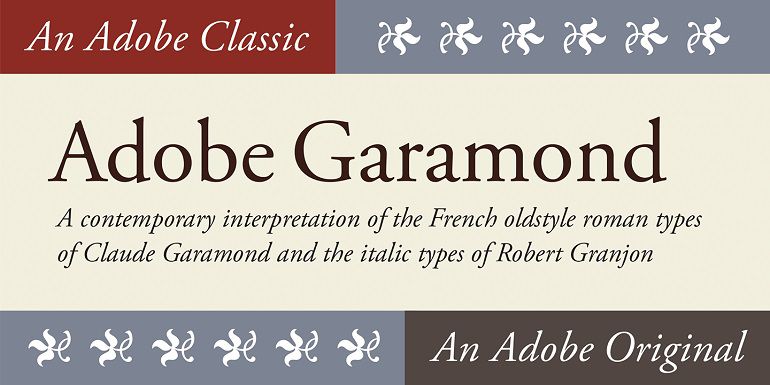
Stellen Sie sich Folgendes vor: Sie haben ein beeindruckendes Briefkopfdesign erstellt, aber irgendetwas stimmt nicht. Die Schriftart.
Es ist nicht nur ein Detail; es ist entscheidend für den ersten Eindruck Ihrer Marke. Hier beginnt die Suche nach den besten Schriftarten für Briefköpfe.
In einer Welt, in der jedes Pixel viel über Ihre Markenidentität aussagt, ist die Wahl der richtigen Schriftart nicht nur eine Designentscheidung; es ist eine Geschäftsstrategie.
Ich habe mich tief in die Welt der Typografie vertieft, von der Eleganz der Serifen bis zum schlanken Reiz der serifenlosen Schriftarten, um Ihnen einen Insider-Einblick in die Auswahl der Schriftarten zu geben.
Dieser Artikel ist nicht nur eine Liste; es ist eine Reise durch die Typografie in der Unternehmensidentität und die Auswirkungen der Schriftartwahl auf das Branding.
Am Ende haben Sie nicht nur eine Handvoll Top-Empfehlungen für Schriftarten, sondern auch ein tiefes Verständnis dafür, wie Schriftartenkombinationen für Geschäftspapiere und Trends in der Briefkopftypografie Ihre Marke aufwerten können.
Ob Sie ein Fan der Klarheit von Helvetica oder der Autorität von Times New Roman sind, dieser Leitfaden bietet für jeden etwas. Machen Sie sich bereit, Ihre Briefköpfe von gewöhnlich zu unvergesslich zu verwandeln.
Die besten Schriftarten für Briefköpfe
| Schriftartname | Designstil | Lesbarkeit | Am besten für | Notizen |
|---|---|---|---|---|
| Quilty Light | Dekorativ | Mittel | Kreative Branchen | Leicht und ausdrucksstark |
| Karoll Modern Serif | Modern/Dekorativ | Hoch | Professionell/Modern | Hoher Kontrast |
| Addington | Übergangs-Serif | Hoch | Unternehmen/Recht | Sophistiziert, altmodisch |
| Garamond | Alt-Serif | Hoch | Verlagswesen/Traditionell | Klassisch und elegant |
| Times New Roman | Übergangs-Serif | Sehr hoch | Geschäft/Allgemeiner Gebrauch | Allgegenwärtig und formell |
| Quiche Sans | Display Sans-serif | Mittel | Mode/Luxusmarken | Hoher Kontrast und schick |
| Mansory | Geometrisch Sans | Mittel | Technik/Moderne Unternehmen | Sauberes, modernes Aussehen |
| Hanken Sans Typeface | Neo-grotesk Sans | Hoch | Start-ups/Moderne Nutzung | Einfach und klar |
| Helvetica | Neo-grotesk Sans | Sehr hoch | Unternehmen/Universell | Neutral und vielseitig |
| Arial | Grotesk Sans | Sehr hoch | Geschäft/Allgemeiner Gebrauch | Weit verbreitet & lesbar |
Empfohlene Schriftarten für Geschäftsbriefe
Lassen Sie uns in das Herz der Sache eintauchen: die Suche nach den besten Schriftarten für Briefköpfe. Es geht darum, die Bühne für die Stimme Ihrer Marke zu bereiten, laut und deutlich zu hören.
Top Serif-Schriftarten
Quilty Light
Es ist wie das leise sprechende Genie im Raum. Elegant, aber zurückhaltend. Perfekt, wenn Sie Raffinesse wünschen, ohne es von den Dächern zu schreien.
Karoll Modern Serif
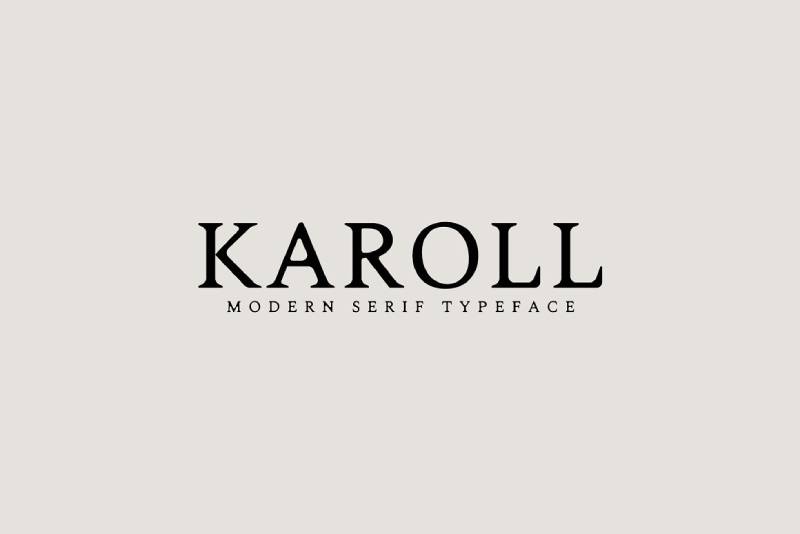
Stellen Sie sich eine Brücke zwischen altmodischem Charme und zeitgenössischem Chic vor. Diese Schriftart sagt: „Wir respektieren die Tradition, aber wir stecken nicht in der Vergangenheit fest.“
Addington
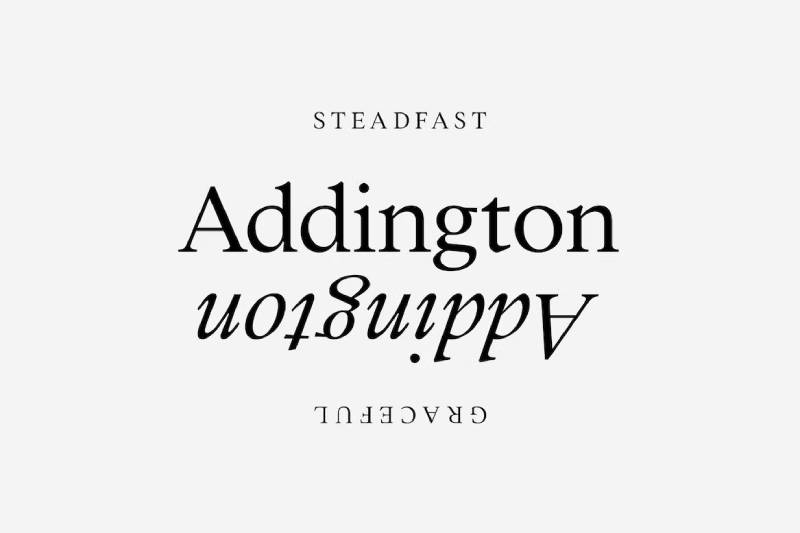
Es ist der Inbegriff des beruflichen Handelns. Denken Sie daran wie an Ihren Anzug für Geschäftstreffen.
Garamond
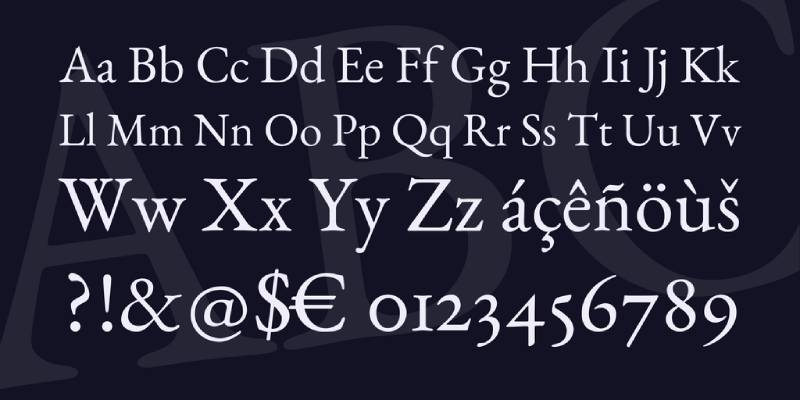
Ein Klassiker. Es ist wie der zeitlose Rat, den Sie von Ihrem Mentor erhalten haben. Zuverlässig, respektiert und immer stilvoll.
Times New Roman
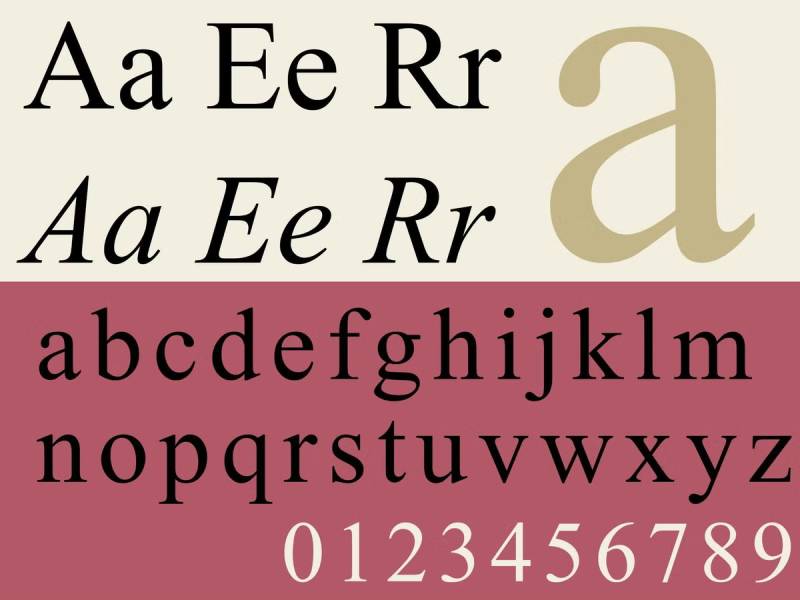
Der alte Verlässliche. Wenn Schriftarten Menschen wären, wäre Times New Roman dieser zuverlässige Freund, der immer da ist, komme was wolle.
Top Sans-Serif-Schriftarten
Quiche Sans
Es ist schick, es ist modern, es ist das Äquivalent zu einem minimalistischen, hochmodernen Büro. Ideal für zukunftsorientierte Unternehmen.
Mansory
Mutig, ohne aufdringlich zu sein. Mansory ist wie jene Person, die allein durch Betreten eines Raums Aufmerksamkeit erregt.
Hanken Sans Typeface
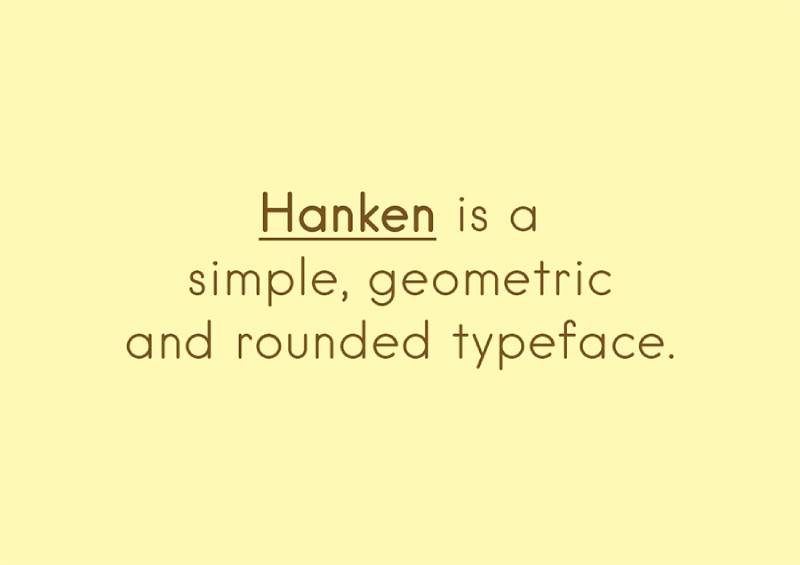
Klare Linien, kein Schnickschnack. Es ist wie der direkte, unkomplizierte Rat, den Sie von Ihrem besten Freund schätzen.
Helvetica
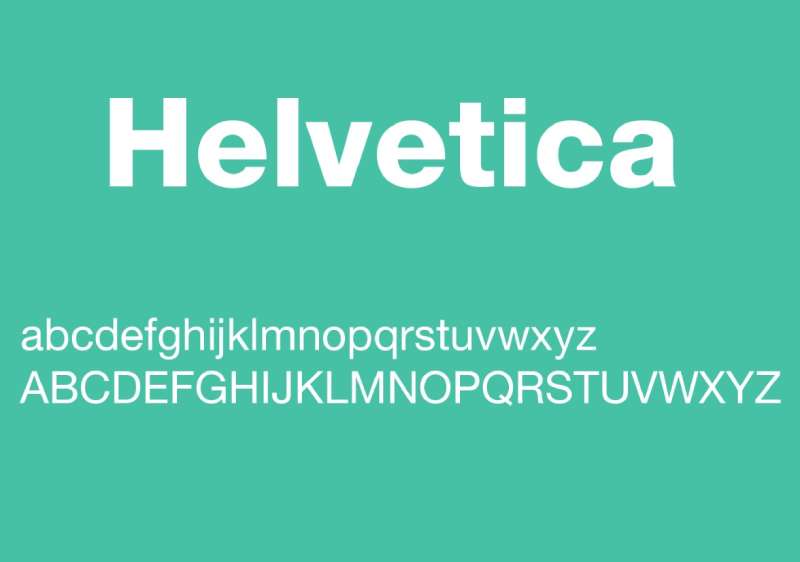
Der König der Sans-Serif. Helvetica ist wie das beliebte Kind in der Schule, das irgendwie mit jedem befreundet ist.
Arial
Denken Sie an Arial als den jüngeren Geschwister von Helvetica. Es ist vertraut, freundlich und vielseitig – eine sichere Wahl für nahezu jede geschäftliche Kommunikation.
Entscheidung zwischen Serif und Sans-Serif-Schriftarten
Serif oder Sans-Serif? Das ist wie die ewige Kaffee-gegen-Tee-Debatte in der Designwelt. Bei der Wahl der besten Schriftarten für Briefköpfe geht es nicht nur um das Aussehen; es geht um die Botschaft, die Sie vermitteln möchten.
Charakteristika von Serif-Schriftarten
Denken Sie an Serif-Schriftarten als die alten Seelen der Typografie. Sie haben diese kleinen Füße (Serifs) an den Enden ihrer Buchstaben. Warum ist das wichtig? Weil diese kleinen Linien Ihrer Briefkopf eine traditionelle, fast autoritative Ausstrahlung verleihen. Stellen Sie sich Times New Roman oder Garamond vor – sie sind wie dieser eine Freund, auf den immer Verlass ist. Serif-Schriftarten eignen sich hervorragend, wenn Sie sagen möchten: „Hey, wir sind etabliert, professionell und vertrauenswürdig.“